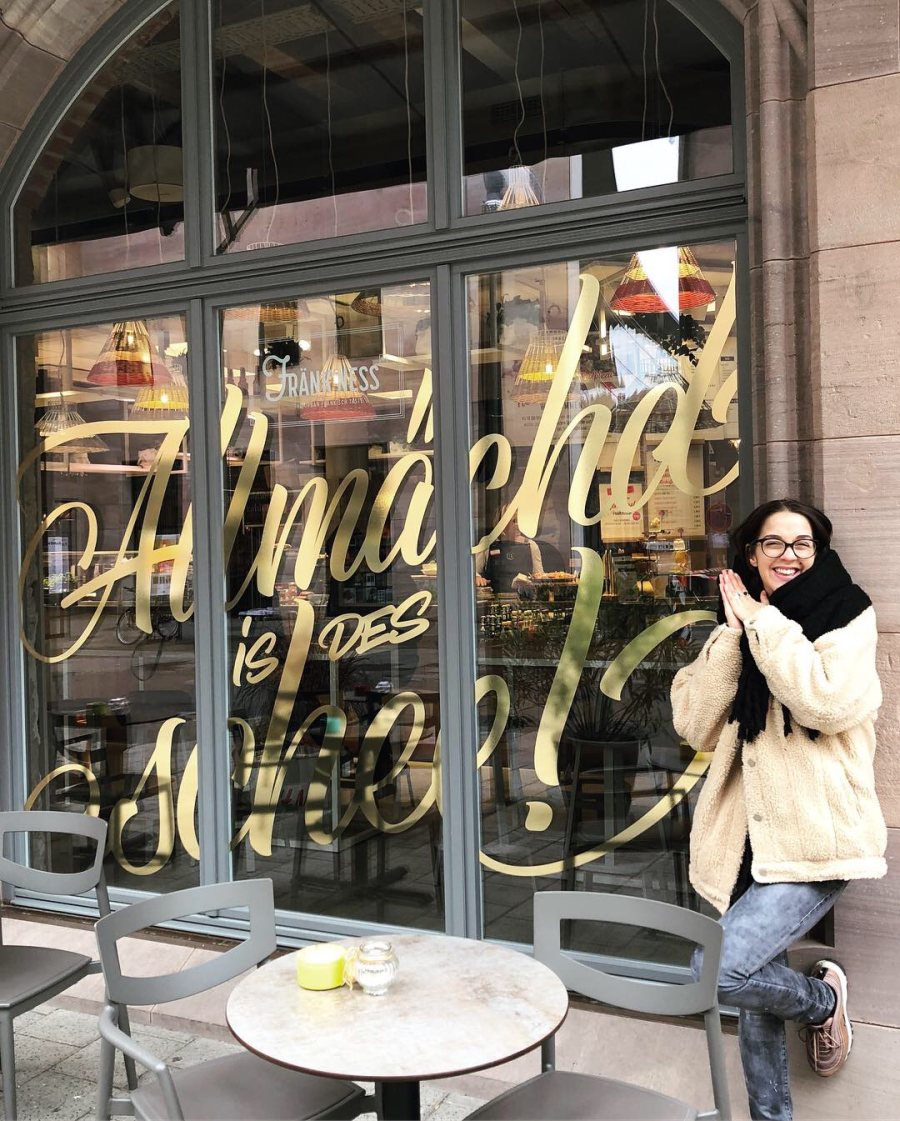
Hannah Rabenstein. Groß gedacht, locker gemacht
Hannah Rabenstein. Groß gedacht, locker gemacht.
Ein Porträt über Buchstabenlust, Räume als Leinwand – und einen kleinen Begleiter aus dem Etui.
Wenn Hannah Rabenstein arbeitet, wird Schrift zur Haltung. Mal leise auf Papier, mal laut auf Wänden. Immer mit Gefühl, Humor und einer Ruhe, die Tempo macht. Und irgendwo zwischen Skizzenbuch und Schaufenster liegt er bereit: ein Werkzeug, das mehr kann als Linie.
Wo Schrift den Raum verändert
Wer Hannah beim Arbeiten zusieht, versteht schnell: Hier schreibt niemand nur schön. Hier nimmt Schrift Platz ein. Auf Tafeln. Auf Glas. An Fassaden. In Innenräumen. Hannah macht Buchstaben zu Bewohnern eines Ortes. Und der Ort bedankt sich, indem er anders wirkt. Freundlicher. Klarer. Manchmal lauter, manchmal feiner. Immer ein Unikat.
Diese Lust an Fläche und Format ist kein Zufall. Sie liebt das Großflächige, doch ihr Weg dorthin beginnt oft klein. Mit einer Notiz. Einem Scribble. Ein paar Pfeilen, die sagen, wo später Dynamik entsteht. Was dann folgt, ist ein Wechselspiel aus Planung und Instinkt. Aus Maßband und Bauchgefühl. Aus Handwerk und Haltung.
Von der Typo zur Tafel
Hannah kommt aus der Typografie, studierte Design an der TH Nürnberg und arbeitet seit 2014 selbstständig. Das erklärt die saubere Sprache ihrer Arbeiten: Sie denkt in Formen, Zwischenräumen, Rhythmus. Ob Handschrift, Hand Lettering oder Kalligrafie – die Mittel wechseln je nach Aufgabe. Die Liebe bleibt die gleiche. Buchstaben sind omnipräsent, sagt sie. Man muss nur hinschauen.
Die Projekte sind vielfältig. Papier, Leinwand, Schaufenster, Fahrzeuge, Möbel, Innenwände. Jede Oberfläche fordert ein anderes Werkzeug. Kreide verhält sich anders als Acryl. Folie braucht Präzision. Pinsel fordern Kraft aus dem Arm, Stifte Fingerspitzengefühl. Genau diese Wechsel machen ihre Tage spannend. Und die Ergebnisse zu Einzelstücken.
Skizze. Pause. Entscheidung.
Bevor eine Wand Schrift wird, geschieht das Unsichtbare. Hannah sammelt Worte, Töne, Farben. Dann landet alles im Skizzenbuch. Nicht nur der Inhalt zählt, auch das Tempo. Ein schneller Strich zeigt Richtung. Eine längere Linie verankert das Motiv. Wo später ein Schwung sitzen muss, markiert oft schon ein krummer Pfeil im Notizheft den Puls. Danach folgen Proportionen, Abstände, Hierarchien. Der Rest ist Erfahrung und eine entspannte Konsequenz, die man ihren Arbeiten anmerkt.
Werkzeuge, die bleiben
Hannah liebt gutes Werkzeug. Nichts Lautes. Nichts, das Aufmerksamkeit heischt. Eher Dinge, die da sind, funktionieren und nebenbei schön aussehen. Die Haptik ist für sie kein Luxus, sondern Arbeitsgrundlage. Wenn ein Stift gut in der Hand liegt, wird die Linie mutiger. Wenn das Gewicht stimmt, findet die Hand von selbst ihren Rhythmus.
In ihrem Etui hat ein kleiner Klassiker einen Stammplatz: der Kaweco Liliput in Kupfer. Schwer und geschmeidig zugleich, sagt Hannah. Ein Stift, der mit der Zeit Patina ansetzt und dabei nur besser wird. Termine, Notizen, To-dos – alles wandert damit ins Buch. Und ja, selbst der nüchternste Punkt auf der Liste bekommt so ein bisschen Glanz. Dazu kommt ein Druckbleistift für präzise Skizzen und spontane Entscheidungen über Strichstärken. Kaweco fühlt sich für sie unaufgeregt richtig an. Elegant, präsent, ohne zu drängen. So, wie ein gutes Werkzeug eben sein sollte.
Vom Etui an die Wand
Wie entsteht die Verbindung vom feinen Stift zur großen Fläche Das ist bei Hannah keine Frage von Entweder oder. Der Stift ist das Denken auf Papier. Das große Format ist das Denken im Raum. Was die kleine Skizze verspricht, löst die Wand ein. Linien werden zu Bahnen, Buchstaben zu Bewegungen. Der Pinsel übernimmt, die Kreide probiert, die Hand findet einen Takt. Ein gutes Werkzeug auf dem Tisch macht den Anfang leichter. Ein gutes Werkzeug an der Wand macht das Ergebnis klarer.
In der Umsetzung zählt für Hannah die Balance. Zwischen Präzision und Patina. Zwischen sauberer Kante und sichtbarem Handzug. Nichts ist steril. Alles hat Spur. Wer nahe an eine ihrer Arbeiten tritt, sieht kleine Entscheidungen, die den Unterschied machen. Eine Spur mehr Druck im Abstrich. Ein Mikroabstand mehr Luft. Ein Hauch von Überlappung, der Tiefe schafft.
Material als Mitspieler
Hannahs Ton ist locker, ihre Arbeiten tragen oft einen freundlichen Unterton. Ein Mural darf strahlen, eine Tafel charmant sein, ein Schaufenster sogar ein Zwinkern haben. Der Humor ist da, aber nie laut. Er stützt den Inhalt, statt ihn zu übertönen. Vielleicht liegt es daran, dass sie sich selbst nie zu ernst nimmt und das Material dafür umso ernster. Material ist für sie nämlich kein Mittel zum Zweck, sondern Mitspieler: Kreide, Acryl, Pinsel, Folie, Marker. Jeder Einsatz lässt Schrift an einem anderen Punkt atmen. Papier nimmt fein an, Glas lässt die Linie schweben, Tafeloberflächen bringen Körnung. Werkzeuge wie der Kaweco Liliput in Kupfer oder ein solider Druckbleistift geben der Skizze ihr Fundament. Was leise beginnt, wächst organisch in den Raum und trägt später den Klang eines Ortes.
Das Handwerk, das bleibt